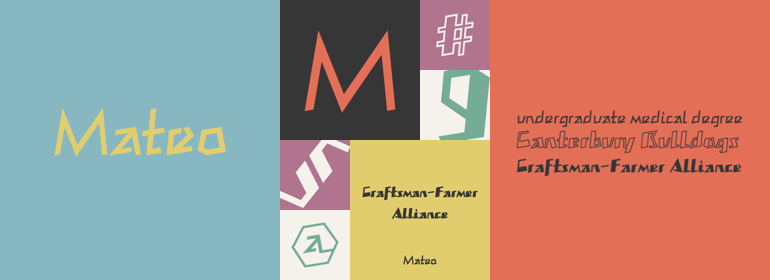
Mateo™
Linotype Mateo字体是Take Type 字体库的一部分,该字库包含了从1994年至1997年Linotype的International Digital Type Design Contest的获奖作品。Jürgen Ellenberger的字体涵盖了三种风格:Roman,Bold以及Outline。Mateo的字符完全由线条组成,使字体看起来非常有棱角。然而,Mateo字体保留了一种手写的风格,有点像之前在小学的木制课桌上留下的涂鸦。Bold和Outline样式更强调笔画,但保留了棱角分明、特意不规则的外观。Roman最适合较小的文本,而Bold和Outline最适合标题。
Linotype Mateo font is part of the Take Type Library, which features the winners of Linotype's International Digital Type Design Contest from 1994 to 1997. Jürgen Ellenberger included three styles in his font, roman, bold and outline. The characters of Mateo consist exclusively of lines, giving the font an extremely angular look. However, Mateo font retains a certain handwritten style somewhat reminiscent of the graffiti left on wooden grade school desks by previous classes. The bold and outline styles have emphasized stroke contrasts but keep the angular, consciously irregular look. The roman style is best for smaller texts and the bold and outlines styles for headlines.